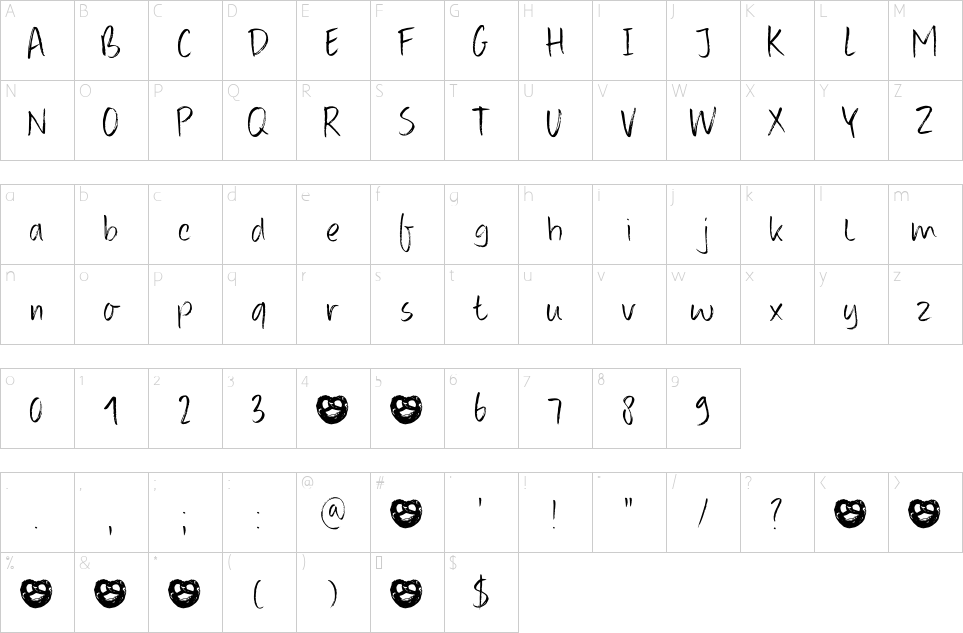
Descubra a delícia no mundo das fontes com a DK Konditorei Font, uma criação delicada para designers amadores e profissionais. Desenvolvida por Hanoded, esta elegante fonte gráfica foi projetada especialmente para adicionar um toque de frescura aos seus designs. Com sua graça natural e detalhes refinados, DK Konditorei é perfeita para qualquer projeto que você esteja planejando, seja ele um layout web, design de mídia ou até mesmo uma capa de livro. Com a facilidade de download em apenas duas cliques, esta fonte tornará seu trabalho mais criativo e divertido. Ao todo, mais de 10 mil downloads atestam o encanto desta fonte de qualidade que traz um toque único ao design. Se você está procurando por uma fonte gráfica perfeita para personalizar seus projetos sem comprometer a essência do seu trabalho, DK Konditorei é definitivamente a escolha certa para incluir na sua biblioteca de recursos gráficos.